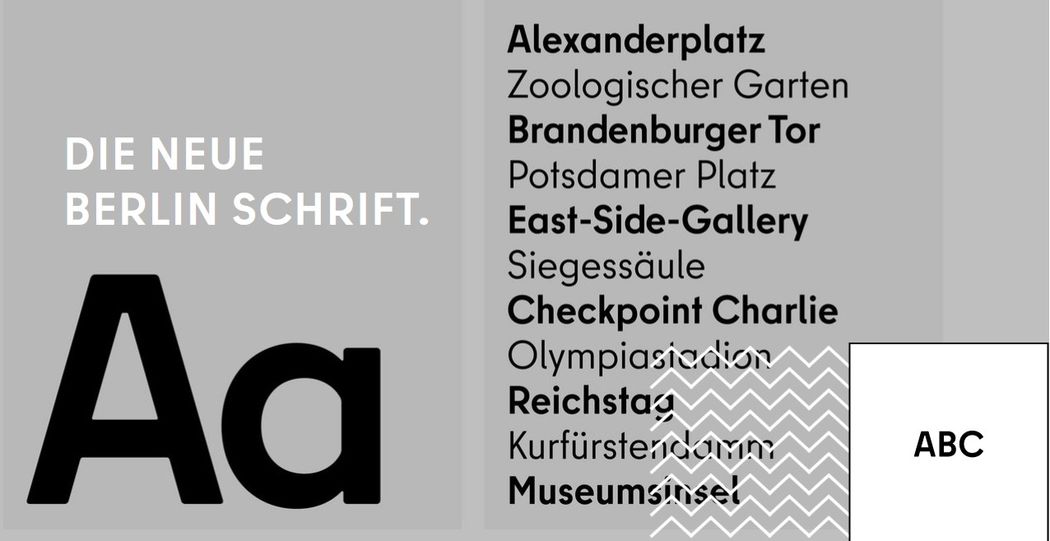
Was versteht man eigentlich unter Berliner Schriftart? Da es sich um keine festgelegte und schon gar nicht um eine geschützte Bezeichnung handelt, gibt es hier jede Menge Interpretationsspielraum. Um ein möglichst breites Feld abzudecken, stellen wir Ihnen die offizielle Berlin-Schrift und Fonts vor, die in der Hauptstadt entstanden sind oder mit ihr zu tun haben.
Die offizielle Berliner Schriftart
Auf der Homepage Wir.Berlin stellt die Stadt ihre offizielle Typografie vor. „Unsere Schrift aus Berlin und für Berlin“, heißt es da. „Inspiriert durch die Schriftenlandschaft der U-Bahn-Stationen und Straßenschilder Berlins. Eine moderne Schrift, mit Anklängen an den geometrisch anmutenden Stil der Schriften aus den 1920er Jahren, entwickelt für die heutigen Anforderungen der Markenkommunikation.“
Berliner Schriftart offiziell
Berliner Schriftart – gratis zur kommerziellen Nutzung
Berliner SchriftartSebaldus Gotisch
Ist gotisch, die Vorlage dazu aber nicht ganz so alt: Ein Unternehmensschriftzug der Berliner Schriftgießerei H. Berthold AG aus dem Jahr 1926 stand Pate.
Berliner SchriftartBerolina
Jugendstil in seiner Reinform: Die Original Berolina erschien um 1900 bei der Gießerei Wilhelm Gronau in Berlin-Schöneberg.
Berliner SchriftartAdmiral CAT
Das Vorbild zu Admiral CAT stammt aus der ehemaligen Berliner Schriftgießerei Wilhelm Wöllmers, die sich auf Werbeschriften in großen Schriftgraden spezialisiert hatte.
Midroba
MITROPA (MITteleuROPäische Schlaf- und Speisewagen Aktiengesellschaft) wurde 1916 in Berlin gegründet, um Bahnreisende zu bewirten. Der Font Midroba hat eine leichte Namensänderung erfahren, sieht dem Original-Schriftzug aber sehr ähnlich.
Materhorn NF
Materhorn NF ist laut seinem Designer „ein perfektes Beispiel für den Gebrauchsgraphik-Stil der 1920er Jahre“. Der Font existiert auch unter dem Begriff Berlin Deco. Dieser Name passt im Prinzip besser, zeigt er doch gleich Herkunft und Stil an. In letzteren mischen sich auch Elemente der deutschen Frakturschrift.
Berlin Email
Gemeint ist hier nicht die elektronische Post (E-Mail). Vielmehr weckt der Font Erinnerungen an Schriften auf alten Schildern aus Emaille (alternative Schreibweise: Email). Deshalb ist diese Berliner Schriftart auch platzsparend schmal.
Berliner SchriftartBerlin
Der brasilianische Designer hat dem Berlin-Thema gleich vier verschiedene Fonts gewidmet. Wir stellen die drei anderen Berlin-Fonts im Anschluss an diesen vor.
Berliner SchriftartBerlina
Wie bei seinen anderen Berlin-Fonts ließ sich Antonio Rodrigues Jr hier von den klassischen geometrischen Schriften zu Beginn des 20. Jahrhunderts inspirieren.
Slaberlin
Mit Slaberlin präsentiert Antonio Rodrigues Jr die einzige Serifenschrift unter seinen Berlin-Fonts.
Uberlin
Der modernste unter Rodrigues Jrs Berlin-Fonts besitzt keine Kleinbuchstaben. Wie die anderen drei Schriftarten derselben Gruppe sind drei Schriftschnitte (bei Berlin zusätzlich auch Kursiv) herunterladbar.